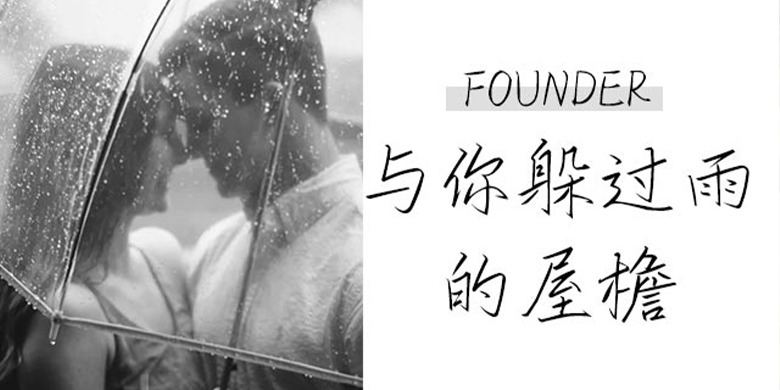
方正手迹-躲雨的屋檐
方正手迹-躲雨的屋檐,这款字体结构工整、笔画清晰,兼顾美观与易读性,适用于标题、正文、海报、包装、LOGO 等多种场景。字形优雅稳定,风格百搭耐看,适配日常排版与创意设计,让文字呈现更舒适、更具质感。方正手迹-躲雨的屋檐一笔一画,皆是细节,以均衡的比例、流畅的线条打造舒适视觉体验,字形端正大气,风格简约现代。无论是商业设计、品牌宣传还是日常排版,都能轻松驾驭,让文字更有格调与力量。方正手迹-躲雨的屋檐字体下载。
行笔一笔一画,字形方正,整体横线呈向下弯曲的势头,宛如水波纹般美丽动人,阅读性强。适用于少年儿童类的书刊、品牌广告和产品包装设计,以及社交网络的个性化用字。